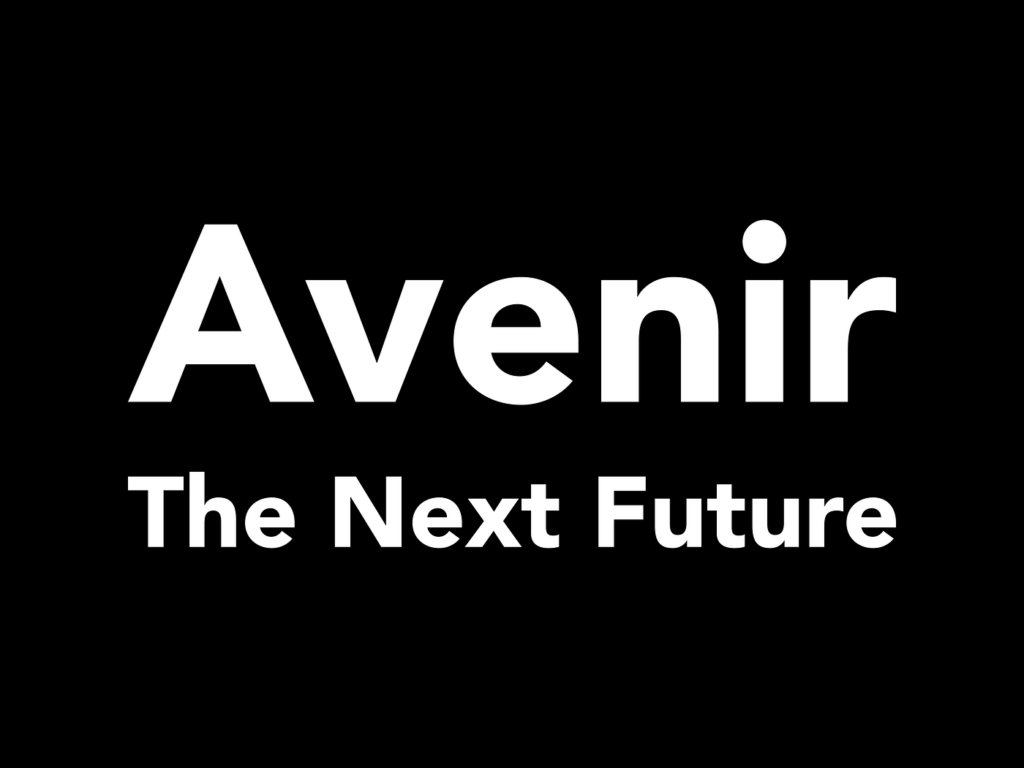
Font Avenir là font chữ sans-serif geometric humanist được thiết kế bởi Adrian Frutiger năm 1988, được sử dụng rộng rãi trong thiết kế bao bì cao cấp, túi giấy thương hiệu và in ấn corporate. Avenir font với phong cách thanh lịch, minimalist là lựa chọn hàng đầu của Apple, LinkedIn, Adobe và nhiều tập đoàn lớn.
Font Avenir là gì?
Font Avenir được thiết kế năm 1988 bởi Adrian Frutiger – một trong những nhà thiết kế font vĩ đại nhất thế kỷ 20 (cũng là người tạo ra Frutiger, Univers). Tên “Avenir” trong tiếng Pháp có nghĩa là “tương lai” – thể hiện tầm nhìn của Frutiger về một font chữ vượt thời gian.
Avenir thuộc họ geometric sans-serif nhưng với nét humanist – kết hợp sự cân đối toán học của geometric với sự ấm áp của humanist. Điều này khiến Avenir vừa hiện đại vừa thân thiện, vừa chuyên nghiệp vừa dễ tiếp cận.
Đặc điểm nhận diện Avenir:
- Geometric nhưng humanist: Chữ O gần tròn hoàn hảo nhưng vẫn có chút biến thể nhẹ, tạo sự ấm áp.
- Nét chữ cân đối: Độ dày nét đồng đều, khoảng cách chữ hoàn hảo.
- Thanh lịch, minimalist: Đơn giản nhưng tinh tế, không một nét thừa.
- Dễ đọc ở mọi kích thước: Từ body text 8pt đến tiêu đề 72pt đều rõ ràng.
Các thương hiệu lớn sử dụng Avenir:
- Apple – sử dụng Avenir Next cho nhiều tài liệu marketing
- LinkedIn – font chính của platform (trước khi chuyển sang custom font)
- Adobe – một số sản phẩm và marketing materials
- Showtime – kênh truyền hình Mỹ
- Amsterdam – city branding
Các dòng font Avenir:
- Avenir (gốc 1988): Có 6 weight: Light, Book, Roman, Medium, Heavy, Black. Mỗi weight có cả Oblique.
- Avenir Next (2004): Phiên bản cải tiến với 12 weight, hỗ trợ ngôn ngữ tốt hơn.
- Avenir Next Condensed: Phiên bản condensed tiết kiệm không gian.
- Avenir Next Rounded: Phiên bản bo tròn góc, thân thiện hơn.
Bảng tổng hợp font avenir next việt hóa và các phiên bản:
Tên phiên bản |
Font weight |
Ứng dụng in ấn tốt nhất |
Avenir Light |
300 | Catalogue cao cấp, body text nhẹ nhàng |
Avenir Book |
400 | Mô tả sản phẩm, thông tin bao bì (8-12pt) |
Avenir Roman |
450 | Body text chuẩn, brochure doanh nghiệp |
Avenir Medium |
500 | Tiêu đề phụ, tên sản phẩm trên túi giấy. |
Avenir Heavy |
800 | Logo thương hiệu, slogan chính (14-24pt) |
Avenir Black |
900 | Poster khổ lớn, standee, tiêu đề nổi bật |
Avenir Next Condensed |
Multiple weights | Tiêu đề hẹp, tiết kiệm không gian |
Ứng dụng Avenir trong bao bì cao cấp
Font Avenir mang phong cách thanh lịch, minimalist được ưa chuộng trong thiết kế cao cấp:
- Vừa hiện đại vừa ấm áp: Khác với font geometric lạnh lùng, Avenir có nét humanist tạo cảm giác gần gũi nhưng vẫn chuyên nghiệp.
- Minimalist không đơn điệu: Font đơn giản nhưng có tính cách riêng, không nhàm chán như Arial hay Helvetica.
- Phù hợp thương hiệu lifestyle: Apple, LinkedIn chọn Avenir vì nó tạo cảm giác accessible luxury – cao cấp nhưng không xa cách.
- Versatile – đa năng: Avenir phù hợp từ tech, organic, wellness đến thời trang minimalist.
Font Avenir xuất hiện trong nhiều sản phẩm in ấn:
- Bao bì sản phẩm organic: mỹ phẩm natural, thực phẩm hữu cơ, wellness product.
- Túi giấy thương hiệu minimalist: startup, lifestyle brand, concept store.
- Catalogue doanh nghiệp: annual report, company profile, brochure corporate.
- Nhãn sản phẩm cao cấp: nhãn chai rượu vang, nhãn olive oil, specialty coffee.
- Hộp quà tặng: gift box minimalist, subscription box.
- Menu nhà hàng fine-casual: bistro, cafe specialty, farm-to-table restaurant.
- Brochure bất động sản: căn hộ cao cấp, condotel, resort.
- Name card chuyên nghiệp: architect, designer, consultant.
3. Font nào giống Avenir nhất và miễn phí?
Nunito từ Google Fonts giống Avenir nhất (90%), cùng geometric humanist với 14 weight đầy đủ. Quicksand cũng rất giống và thân thiện hơn.
Font Avenir thanh lịch, minimalist phù hợp bao bì cao cấp. Dùng Nunito, Quicksand thay thế miễn phí an toàn cho in ấn.